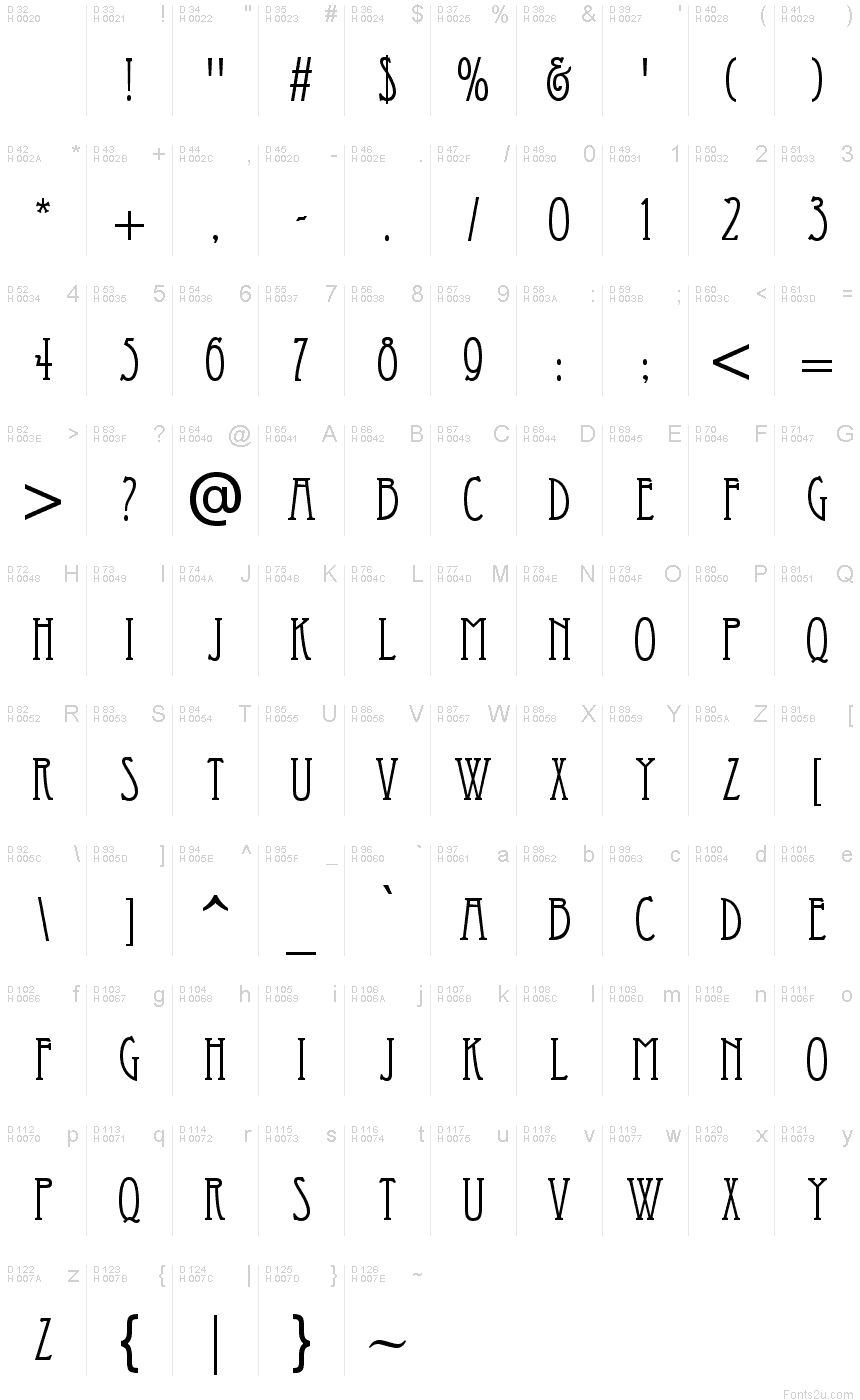
Eccentrical od Please Steal This Font to darmowy, dekoracyjny krój retro o wyrazistym charakterze, którego litery wyglądają, jakby zostały delikatnie wyciągnięte w górę. Smukłe, pionowe formy, zakręcone końcówki i lekko kołyszący się rytm nadają każdemu słowu energię przypominającą plakaty cyrkowe – jest zabawnie, nieco dziwacznie i bardzo zapadająco w pamięć. Kreska wygląda na rysowaną tuszem, a nie sterylną, dzięki czemu nawet jedno słowo złożone dużym stopniem pisma natychmiast przyciąga uwagę.
Dzięki Eccentrical nadasz nagłówkom, plakatom vintage, okładkom książek, menu kawiarnianym, opakowaniom, ulotkom i oryginalnym logotypom silny, teatralny charakter. Ten darmowy font najlepiej prezentuje się w większych rozmiarach; w tekście głównym zestaw go z prostym, geometrycznym bezszeryfowym krojem, aby zrównoważyć jego ekscentryczny urok.
Please Steal This Font
Eccentrical